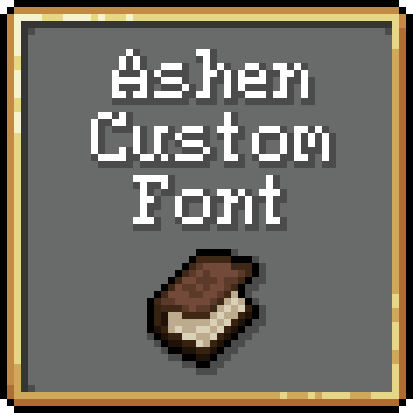
Ashen 16x Custom Font
Текстурпак Ashen 16x Custom Font заменяет стандартный шрифт Майнкрафт на новый, средневеково-фэнтезийный шрифт с засечками. Полная поддержка кириллицы и всех игровых алфавитов.
Ashen 16x Custom Font - это не просто очередной шрифт для Майнкрафт, а полноценная замена всей ванильной типографики. Если тебе надоел стандартный шрифт игры и хочется чего-то более атмосферного, особенно в средневековых или фэнтезийных сборках - этот текстурпак для тебя.
Что это и зачем нужно
В ванильном Майнкрафт шрифт довольно простой и нейтральный. Он не ломает атмосферу, но и не добавляет ей глубины. Ashen 16x Custom Font решает именно эту проблему - он меняет восприятие текста в игре: названия предметов, интерфейс, таблички, книга с пером - всё это начинает выглядеть иначе.
Шрифт с засечками (serif) придаёт игре более серьёзный, "древний" вид. Особенно круто он смотрится в сочетании с соответствующими ресурспаками вроде Ashen 16x, для которого он изначально и создавался.
Особенности
• Полный набор символов - в отличие от многих других шрифтовых ресурспаков, этот не ограничивается латиницей. Он поддерживает всё, что можно ввести в ванильном Майнкрафт: кириллицу, алфавит Иллиджеров, Стандартный Галактический (алфавит стола зачарований) и другие.
• Отдельный аддон - раньше шрифт был частью основного пака Ashen 16x, но автор вынес его отдельно. Так что можно использовать с любым другим ресурспаком, хоть с ванильным.